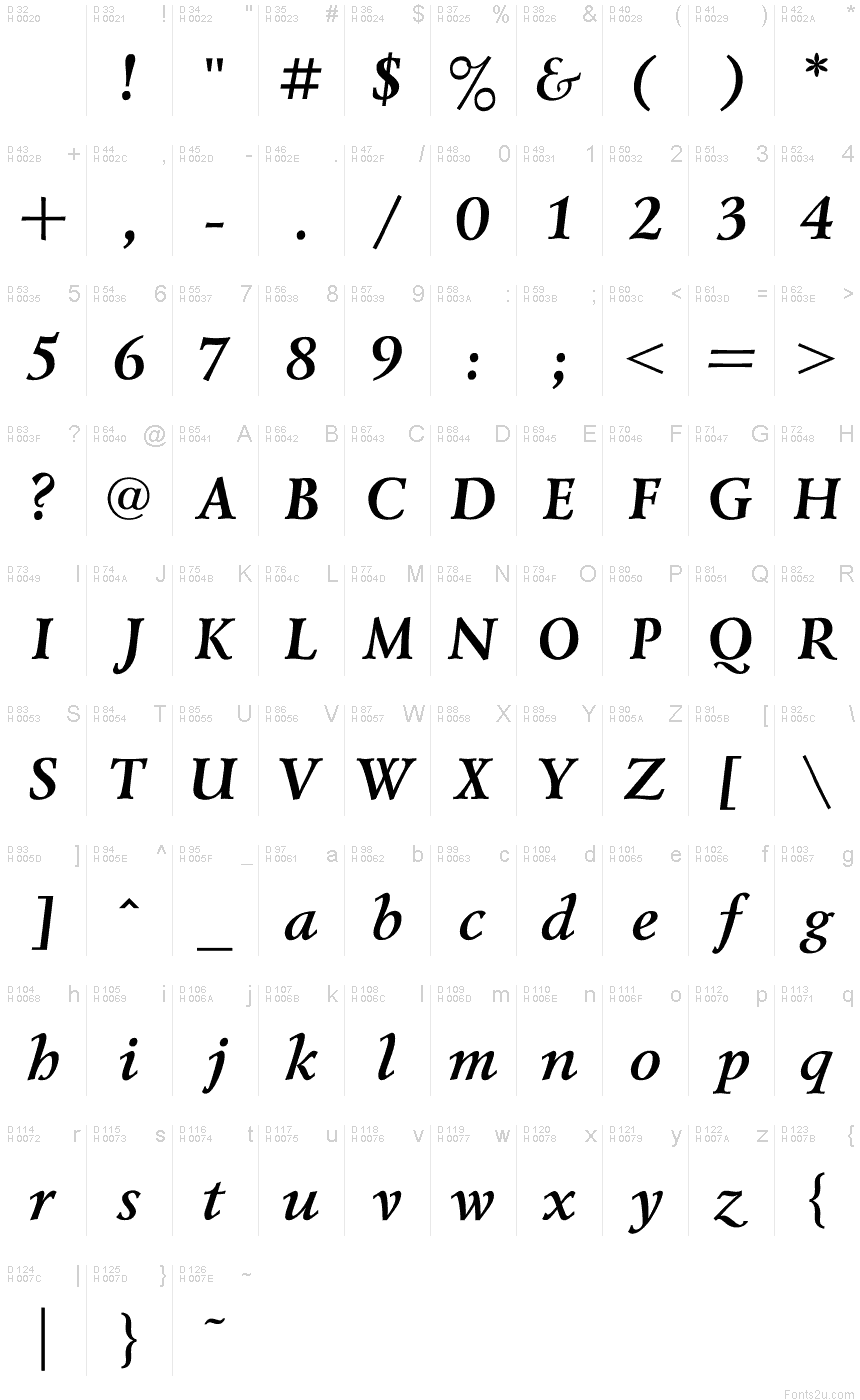
Lazurski Bold Italic
Lazurski Bold Italic od Atech Software to darmowy, kaligraficzny krój szeryfowy o wyrazistym, literackim i staroświeckim charakterze. Litery łączą w sobie szerokie, ciemne pociągnięcia z ostrymi, zwężającymi się końcówkami i wijącymi się wykończeniami, co nadaje alfabetowi niemal renesansowy, grawerowany sznyt, daleki od neutralnej kursywy.
Świetnie sprawdzi się na okładkach książek, w nagłówkach magazynów, w brandingu restauracji, na etykietach win czy plakatach inspirowanych dawnymi epokami, gdzie tytuł potrzebuje dynamiki bez utraty formalnego tonu. Jako darmowy font, idealnie nadaje się również do plansz tytułowych, monogramów i krótkich napisów na opakowaniach, zwłaszcza gdy zależy Ci na tym pełnym energii, kaligraficznym stylu w zaledwie kilku znakach.